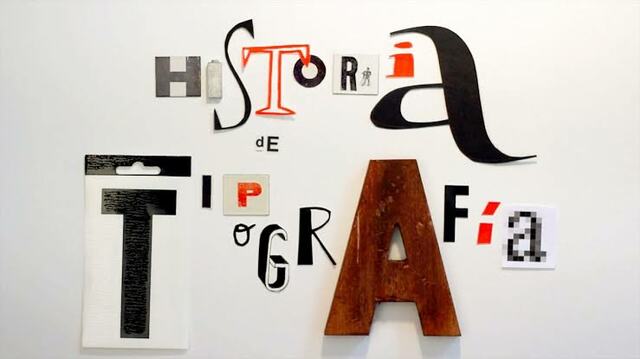
La tipografía como tal surge con la imprenta de Gutemberg, puesto que la tipografía es una manera mecánica describir, y con esta imprenta es la primera vez que se crea escritura de manera mecánica ayudada de los tipos móviles. La imprenta nace en Maguncia en 1450, no esta muy claro si se inventó por la necesidad de avanzar o por la necesidad de crear más libros puesto que cada día había más y más lectores.
Surgió la Linotipia y la monotipia. La primera aparece gracias a Otto Mer Genthaler en 1886, se asemeja a la máquina de escribir, utiliza lingotes que funden las lineas de texto completa, se utilizaba en la prensa. La Monotipia apareció con Tolbert Lansto en 1887, se utilizaba en la industria de los libros, en este caso va letra por letra en vez de por lingotes.
En el 1900 nos topamos con las nuevas vanguardias que conviven con el Art Nouveau (Modernismo en España) muy influenciado por la pintura, y es considerado precursor del diseño gráfico. Se utiliza una tipografía muy de pintura que parece dibujada. Define la belleza del estilo y la línea tradicional.
En este periodo encontramos tipografías características como la Gismonda, Isadora, Perry Gothic y sobretodo la Arnold Böcklin. -
A este periodo pertenece la Arial, se considera que es una copia de la Helvética por ello se le guarda cierta manía, fue un encargo de Windows para ahorrarse los costes de la Helvética de modo que les salía más barato y era parecida, es de 1982
En los años 80 aparecen los primeros ordenadores como el Macintosh además de la primera impresora de la marca hp en el 1984. Con la aparición de los ordenadores nace Page Maker, el primer programa de maquetación, y aparecen fuentes del sistema operativo que eran unas determinadas fuentes para los equipos informáticos.
En 1984 aparece Emigre, una revista que sirvió de respaldo para el punto de encuentro del mundo tipográfico. -
En este periodo comienza el comercio de las tipografías, las fundiciones crean y venden sus tipografías, no solo las crea sino que además las compran. Se crean tipografías nuevas, una fundición de la época es Bitstream, de la cual es característica la Chapter.
1990 Hubo un bum amateur en la tipografía, ya era normal que cualquiera tuviese un ordenador personal. Comienzan a aparecer tipografías de todo tipo, esto se debe a que la gente menos profesional comienzan a meterse en el mundo y a crear su propias tipos las cuales son todas titulares en vez de tipos más profesionales.
Una de las grandes fundiciones internacionales es FSI creada por Murille Brody.